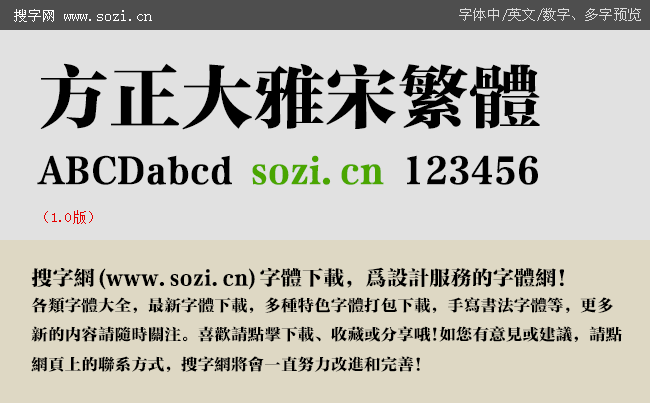
方正大雅宋繁體(FZDYSFW)
搜字網(wǎng)提供一款方正大雅宋繁體中文字體下載,方正大雅宋繁體是一款字形清秀的中文字體,該字體端正大方,結(jié)構(gòu)清晰,效果出眾,常用于產(chǎn)品設(shè)計(jì)、包裝印刷、報(bào)刊雜志、正文標(biāo)題、繪畫創(chuàng)作等廣告設(shè)計(jì)場(chǎng)合使用。